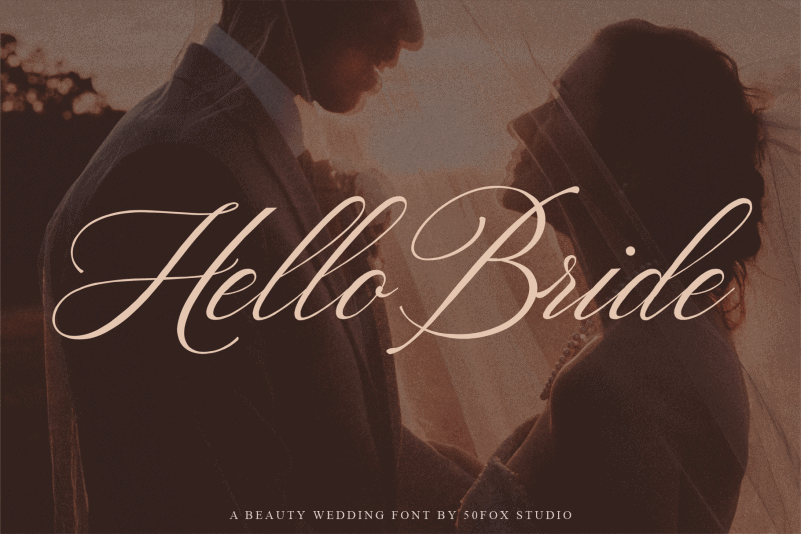
Hello Bride Calligraphy Font – Download Grátis
Esta linda fonte ‘Hello Bride Calligraphy Font’ é perfeita para quem está buscando um toque elegante e sofisticado para suas festas especializadas, especialmente para casamentos de luxo ou cerimônias de compromisso. Esta fonte de calligrafia vem com estilo elegante que complementa perfeitamente o charme das ocasiões mais especiais. Ideal para gráficos nupciais, convites e outros materiais decorativos relacionados a essas celebrações imortais, a ‘Hello Bride Calligraphy Font’ traz uma dose extra de elegância à sua decoração. Seja um convite, um menu ou até mesmo um cartão de agradecimento, esta fonte é perfeita para dar aquele toque único e memorável aos eventos mais românticos. Seja você designer gráfico, editora de blogs nupciais ou profissional do setor de papelaria relacionado ao casamento, esta fonte de calligrafia é um recurso invaluable a sua coleção. Ela não só facilitará o processo de criação de material de evento, mas também adicionará um toque personalizado e único à cada item que você criar com ela.